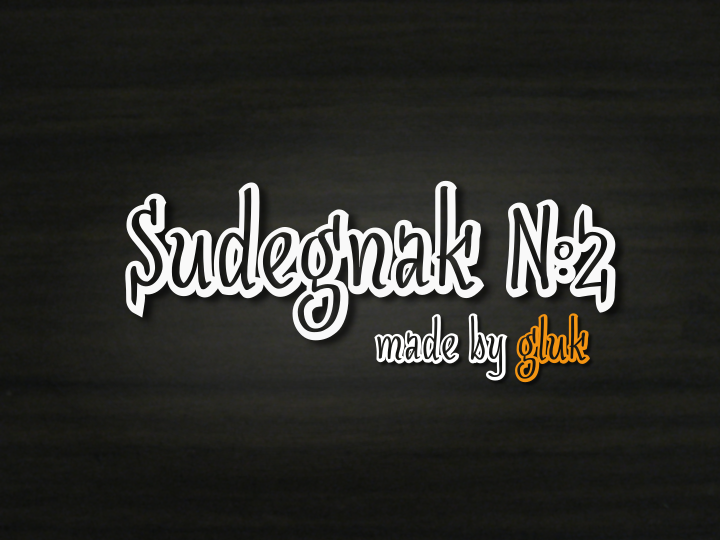
A SudegnakNo2 Font é uma exuberante escolha para qualquer designer que busca um display bold e vibrante na sua próxima criação visual. Criada pelo talentoso Hamilton, esta fonte apresenta linhas robustas e formas assertivas, projetadas para destacar no meio de qualquer tipo de projeto gráfico. Com certeza ideal para títulos chamativos, headlines poderosas ou qualquer elemento que deseja chamar a atenção do público. Seu design é caracterizado por uma tipografia exuberante com linhas robustas e formas vibrantes, adaptada para destacar em qualquer projeto visual. Perfeito para apresentar títulos chamativos, headlines poderosas ou qualquer elemento de destaque na sua criação.